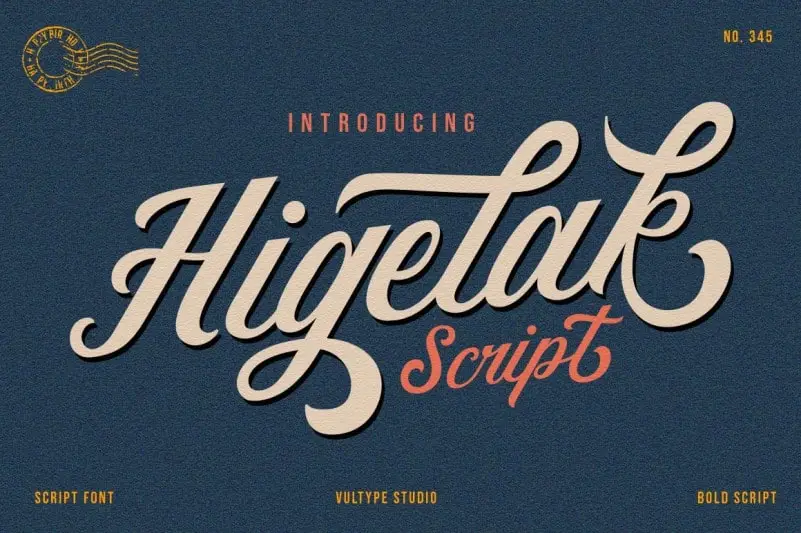
Higelak Script Font surge inspirado nas letras de correspondências antigos, rótulos de cerveja, certificados, bilhetes de estacionamento e desenhos para fita registros dos anos finais do século XIX até o início do século XX. Suas linhas curvas e elegantes remetem a um tempo distante em que essas fontes seriam usadas para imprimir documentos importantes ou promocionar produtos nos ambientes comerciais da época. A Higelak Script é uma paixão para amantes dos estilos manuscritos, oferecendo um toque sofisticado e vintage às suas criações digitais. Seja para adicionar um elemento nostálgico em um design gráfico ou para recriar a atmosfera de escritório comercial do passado, Higelak Script Font é uma escolha inteligente que certamente fará seu trabalho.